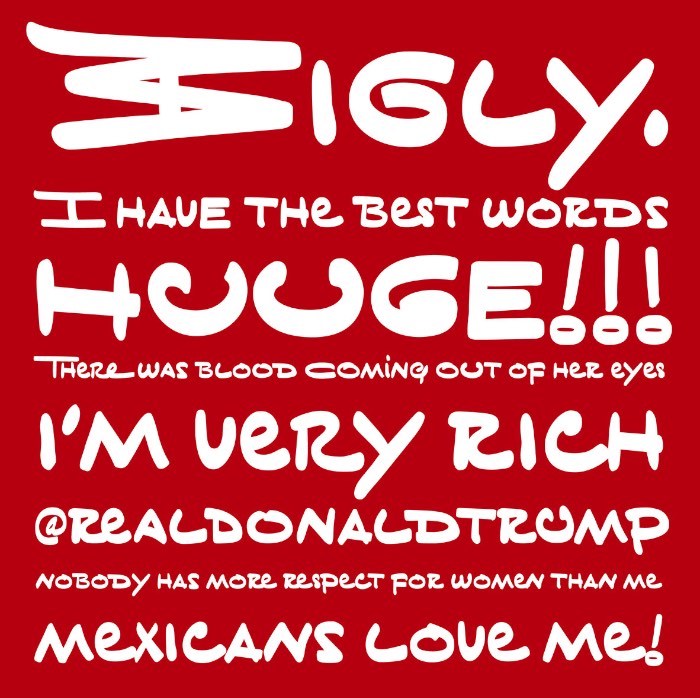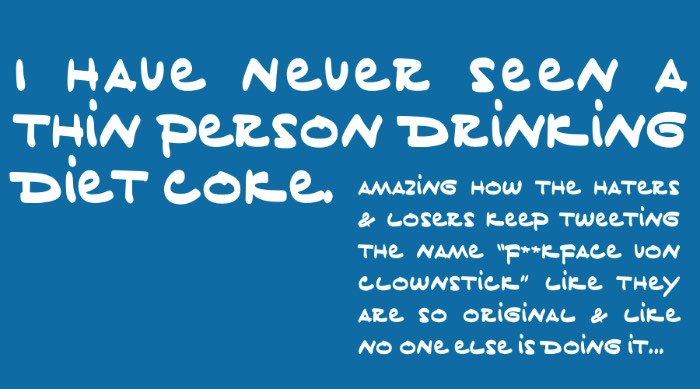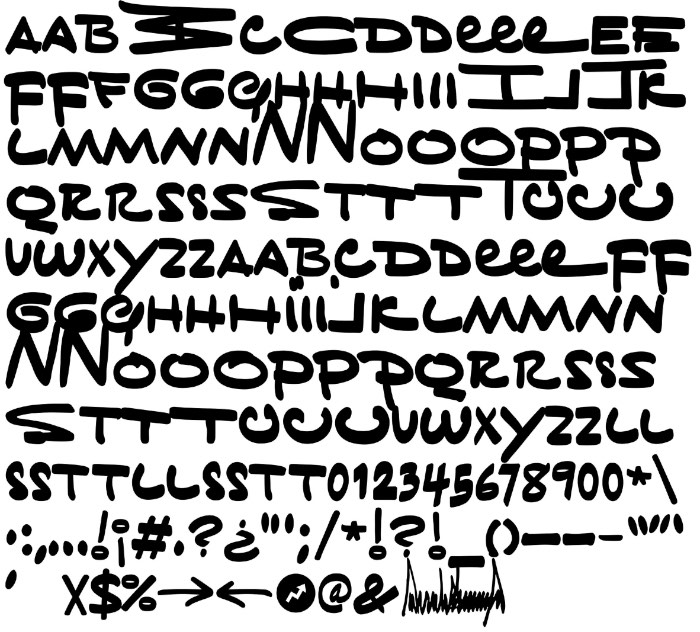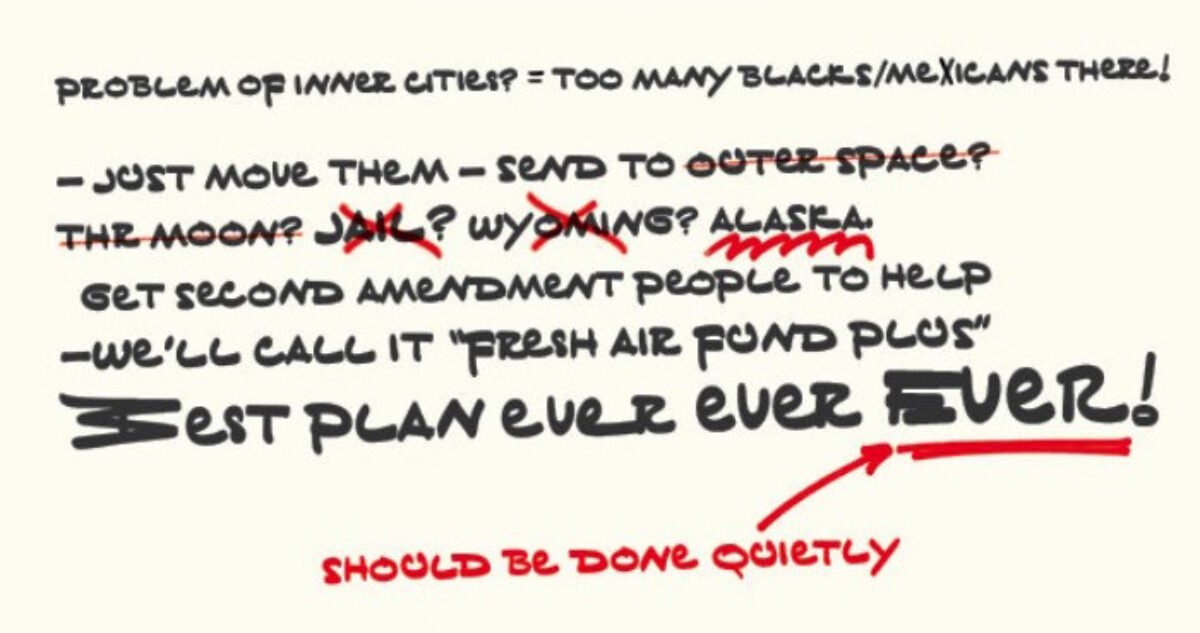
Tiny Hand: Uma Fonte Inspirada em Donald Trump
Tiny Hand é o nome da fonte criada pelo designer Mark Davis a pedido do pessoal do Buzzfeed. Inspirada na letra de mão do candidato a presidência dos Estados Unidos e pseudo milionário Donald Trump, essa fonte foi criado especialmente para um artigo editorial satirizando com suas anotações de pós debate.
Para Mark Davis, o maior desafio de recriar a letra de mão de Donald Trump é como ele segura a caneta de uma forma distinta. Quando a maioria das pessoas segura a caneta em um ângulo de 45º, ele segura de um jeito diferente criando um ângulo de 90º que fica ainda mais peculiar pelo fato dele segurar a caneta pelo extremo final dela. Por culpa disso, suas letras são bem largas e com inícios e fins de letras bem pesadas.
As referências visuais que o designer usou vieram de artigos impressos sobre si mesmo que Donald Trump costuma anotar com seus comentários, sempre muito críticos. Mas, quando algumas letras não existiam, o designer experimentou um pouco como é ser Donald Trump e foi criando o resto das letras.
A ideia por trás de Tiny Hand veio de um dos editores do Buzzfeed, Ben King, que estava pesquisando por referências visuais para um artigo quando teve a ideia de usar da própria letra de mão de Donald Trump para transformar seu artigo em algo mais interessante. Foi ai que entrou o trabalho do designer Mark Davis, que acabou fazendo o design de toda a fonte, mesmo com os problemas que mencionei logo acima.